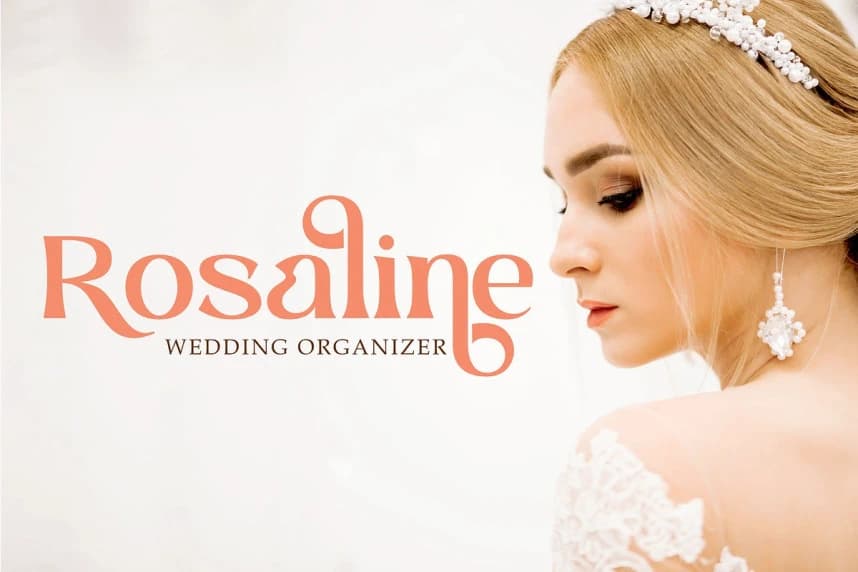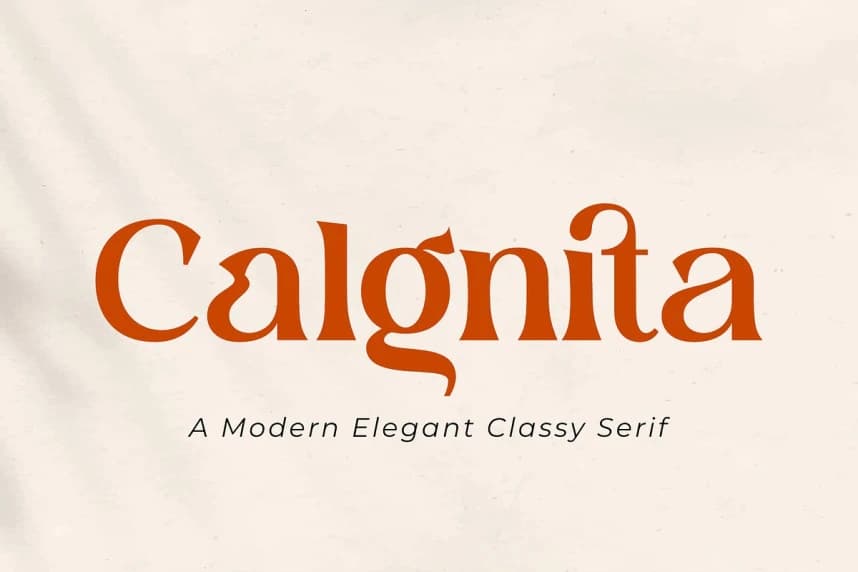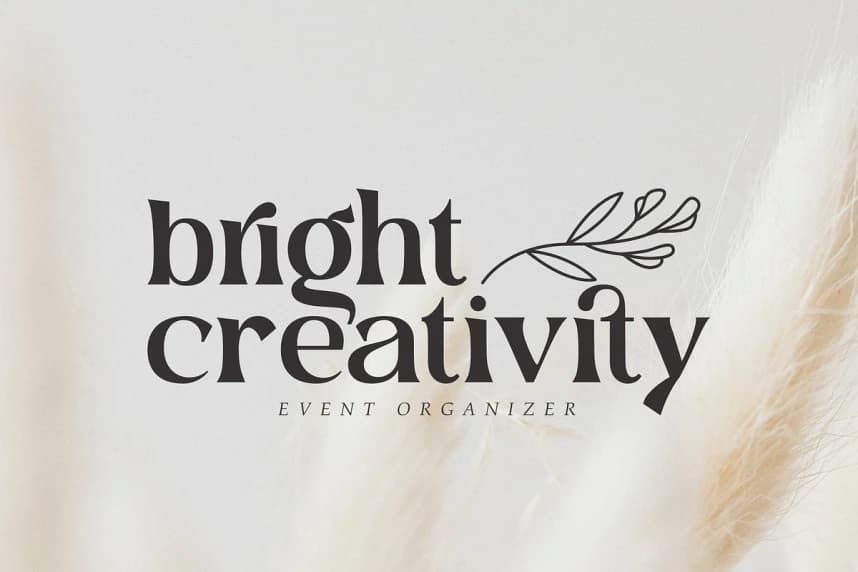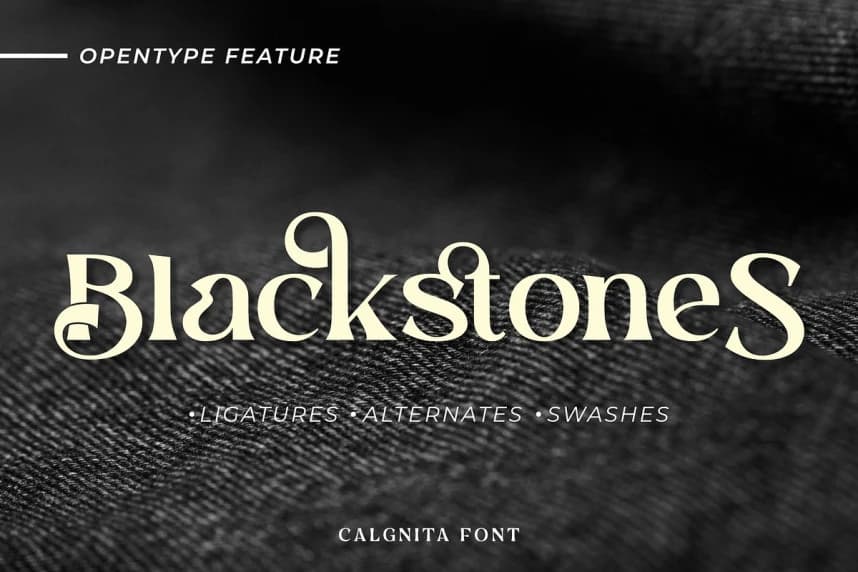
Calgnita Font, zarafeti ve sofistikasyonu yansıtan modern klasik bir serif yazı tipidir. Klasik şekillerine ve rafine eğrilerine sahip olan Calgnita, zamansız tasarımın özüdür ve markalaşma, logotipler ve çeşitli tasarım projeleri için ideal bir seçimdir.
Calgnita Font, zarafet ve inceliği simgeleyen modern klasik bir serif yazı tipidir. Klasik şekilleri ve zarif kıvrımlarıyla Calgnita, zamansız tasarımın simgesidir ve markalaşma, logotipler ve çeşitli tasarım projeleri için ideal bir seçenek sunar.